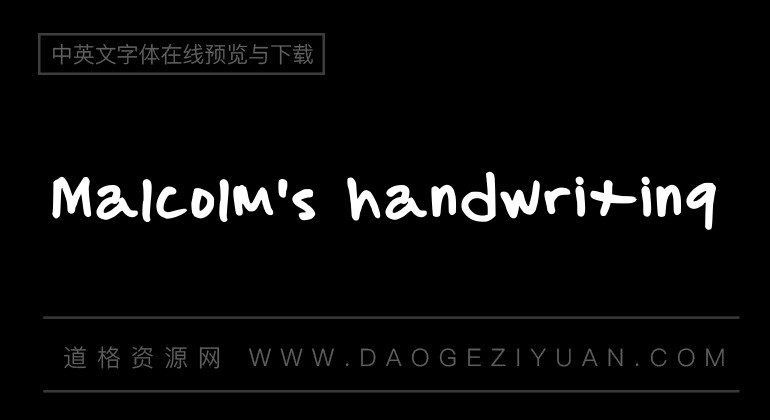
Malcolm's handwriting
Malcolm's handwriting 字体是一款经典的手写字体,由英国设计师 Malcolm Garrett 于1986年设计。它具有流畅的笔画,自然的线条,温柔的曲线,以及清晰的字母形状,是一款极具有现代感的字体。Malcolm's handwriting 字体可以用于广告、标志设计、图书封面、招牌、礼品和卡片等,是给人以温馨感受的字体。
Malcolm's handwriting是一款非常不错的手写艺术字体,具有很好的视觉感,适合于文化类的宣传设计、商业类品牌的广告和产品包装设计以及个性化文字排版等较多场景。